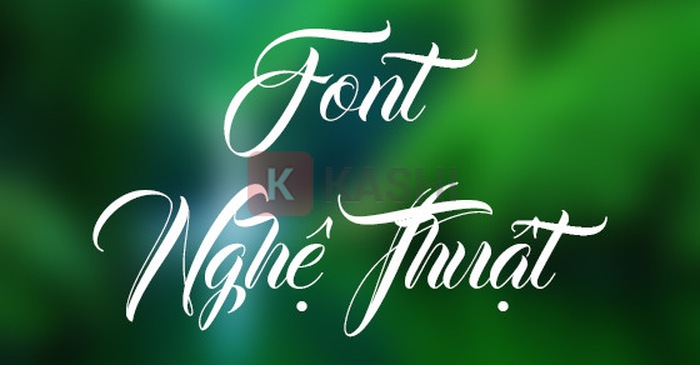
Tổng hợp 100+ Font chữ nghệ thuật đẹp và ấn tượng nhất 2025
Bạn đang tìm kiếm bộ font chữ nghệ thuật độc đáo để thiết kế banner, slogan, poster, in ấn lên áo hoặc phục vụ cho công việc và học tập? Bài viết này trên Thủ Thuật sẽ giới thiệu đến bạn những font chữ nghệ thuật đẹp mắt và chất lượng, cùng với hướng dẫn tạo font chữ nghệ thuật online.
Font chữ nghệ thuật là gì? Font chữ nghệ thuật được thiết kế với các nét cong mềm mại, uyển chuyển và cách điệu độc đáo. Chúng thường được dùng cho tiêu đề, banner, poster để tạo ấn tượng mạnh và thu hút sự chú ý. Các loại font chữ nghệ thuật phổ biến bao gồm Brush, Script và Calligraphy (thư pháp hiện đại). Trong thiết kế đồ họa, font chữ đóng vai trò quan trọng không kém hình ảnh, màu sắc và âm thanh, giúp sản phẩm thiết kế trở nên nổi bật và chuyên nghiệp hơn.
Hướng dẫn tạo Font chữ nghệ thuật online
Nếu bạn muốn sử dụng font chữ nghệ thuật nhanh chóng mà không cần tải về, có thể sử dụng các công cụ tạo font chữ nghệ thuật online như TextFx, Flamingtext, TextPro… Bạn chỉ cần nhập chữ vào ô và sao chép chữ đã được tạo kiểu để sử dụng trong các phần mềm thiết kế đồ họa.
1. Công cụ TEXTFX
TextFx là công cụ tạo chữ nghệ thuật trực tuyến đơn giản và dễ sử dụng. Với nhiều mẫu chữ nghệ thuật có sẵn, bao gồm cả các hiệu ứng giống như poster phim nổi tiếng, TextFx là lựa chọn tuyệt vời cho những ai yêu thích phong cách này.
2. Công cụ FLAMINGTEXT
FLAMINGTEXT là một website giúp tạo font chữ nghệ thuật dễ dàng với giao diện đơn giản, thân thiện với người dùng.
3. Công cụ TEXTPRO
TextPro là một trong những công cụ tạo chữ nghệ thuật online miễn phí phổ biến nhất hiện nay. Các kiểu chữ nghệ thuật trong TextPro được phân chia theo nhiều chủ đề khác nhau như khoa học, thiên nhiên, thực phẩm, giả tưởng…
4. Công cụ CoolText
CoolText mang phong cách cổ điển, phù hợp với nhiều đối tượng. Giao diện trực quan, tốc độ xử lý nhanh và các hiệu ứng chữ được cập nhật liên tục là những điểm cộng của công cụ này.
Tổng hợp các Font chữ nghệ thuật đẹp
Dưới đây là một số font chữ nghệ thuật tiếng Việt đẹp mắt mà bạn có thể tham khảo:
1. Font Antiophie
Font Antiophie mềm mại nhưng vẫn cứng cáp, mang lại sự mới mẻ cho thiết kế. Phù hợp cho banner, bìa sách, tạp chí, poster…
2. Font Ayres
Font Ayres mang nét cổ điển và thanh lịch, phù hợp với nhiều loại thiết kế.
3. Font Badriyah
Font Badriyah là kiểu chữ ký tay phóng khoáng, tạo ấn tượng mạnh mẽ cho thiết kế.
4. Font Badhead
Font Badhead mang phong cách cổ điển phương Tây, phù hợp với các thiết kế mang tính nghệ thuật.
5. Font Bahagia
Font Bahagia đơn giản nhưng cuốn hút với các đường nét rõ ràng, tạo cảm giác dễ chịu cho người nhìn.